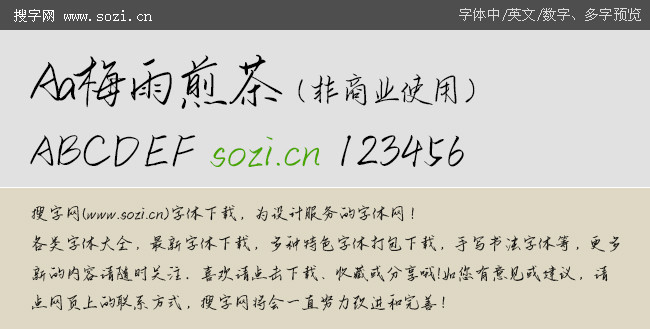
Aa梅雨煎茶
搜字網(wǎng)給大家提供一款A(yù)a梅雨煎茶(非商業(yè)使用)中文字體下載,該字體是一款手寫風(fēng)格的字體,字體筆觸較為纖細(xì)靈動(dòng),字形灑脫,流暢自然,具有很好的視覺感。適合書裝設(shè)計(jì)、包裝設(shè)計(jì)、海報(bào)設(shè)計(jì)等應(yīng)用(此字體為個(gè)人非商用版,商用可以聯(lián)系QQ:1006760504)。